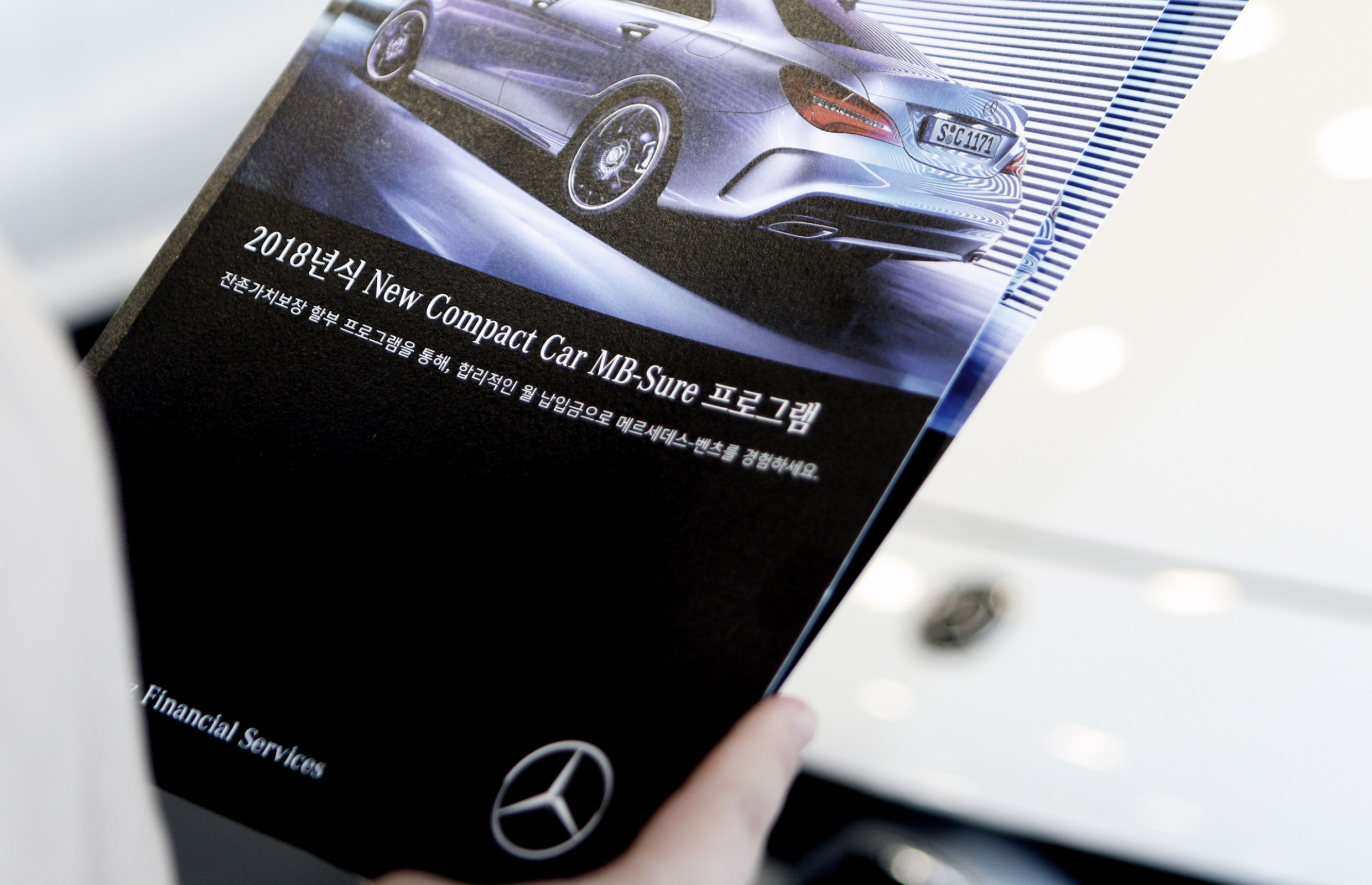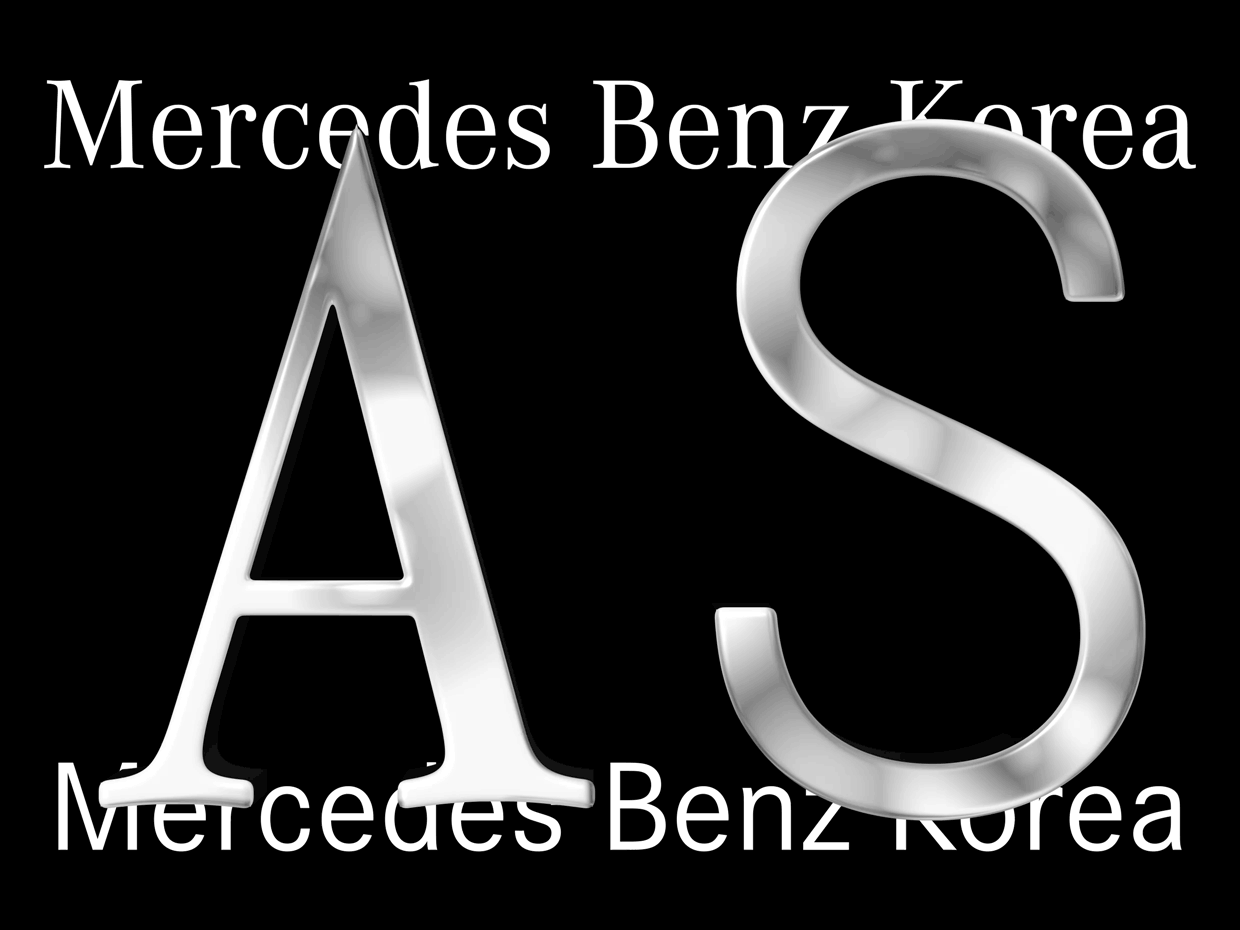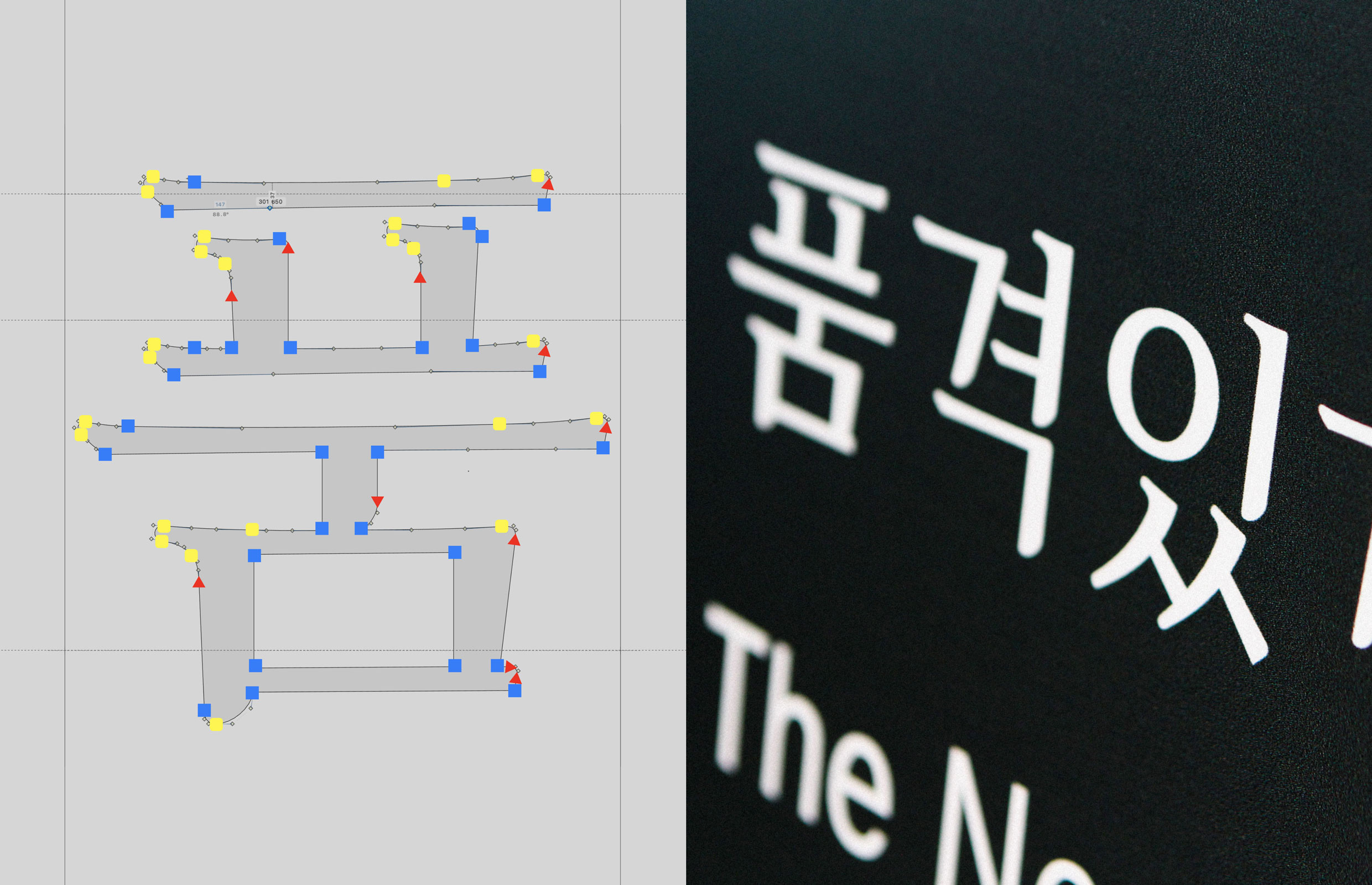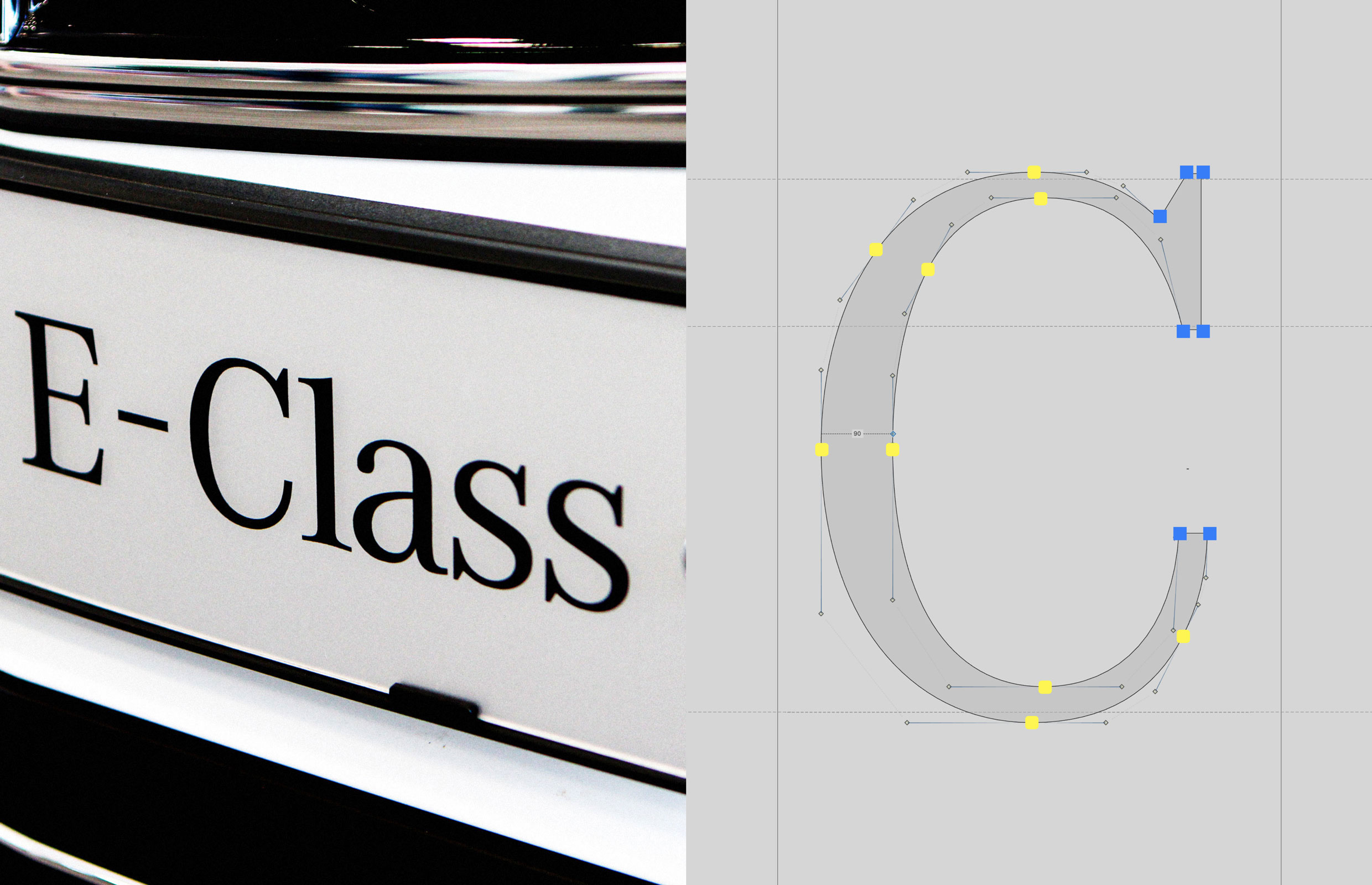
메르세데스 벤츠
메르세데스 벤츠 코리아 [MBK]
메르세데스-벤츠 브랜드 고유의 ‘모던 럭셔리(Modern Luxury)’ 감성을 표현한 전용서체. 명조 계열 ‘MBK CorporateA’는 우아한 품격을, 고딕 계열 ‘MBK CorporateS’는 젊고 역동적인 감각을 상징한다. 두 서체는 메르세데스-벤츠 코리아의 광고 및 내부 커뮤니케이션에 사용되었다.
메르세데스-벤츠 코리아
임광규, 한선주